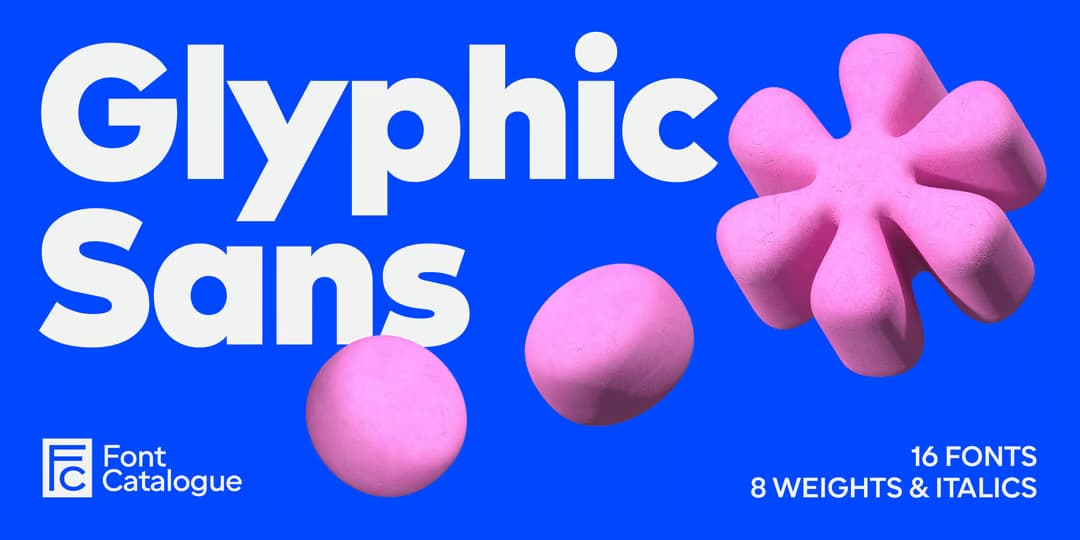
みんな大好きジオメトリックサンセリフ。幾何学的だからこそみんなほぼ同じになってしまうのにこんなに作られ続けるのはなぜだろう。まあそんな事はさておき。どうしても代表的な Futura と比べてしまうが、それと比べて大きめのxハイトとちゃんと曲がった j のフック、ベースラインより上から伸びてる長めの y のディセンダーなど、可読性を考慮したより自然なグリフを心がけている。スッキリして読みやすく汎用性の高い書体だろう。8ウェイト。ただいま60%オフセール中。